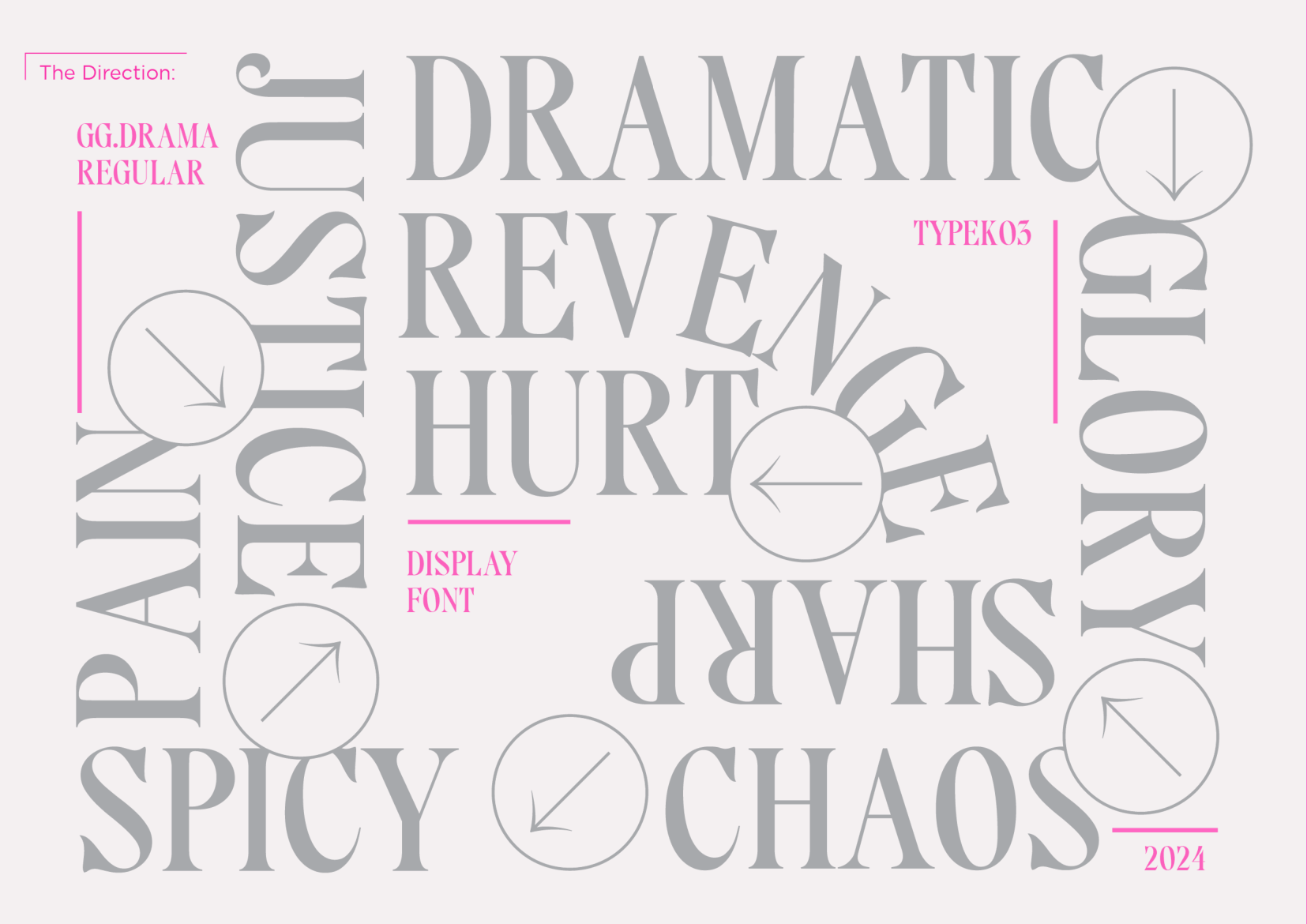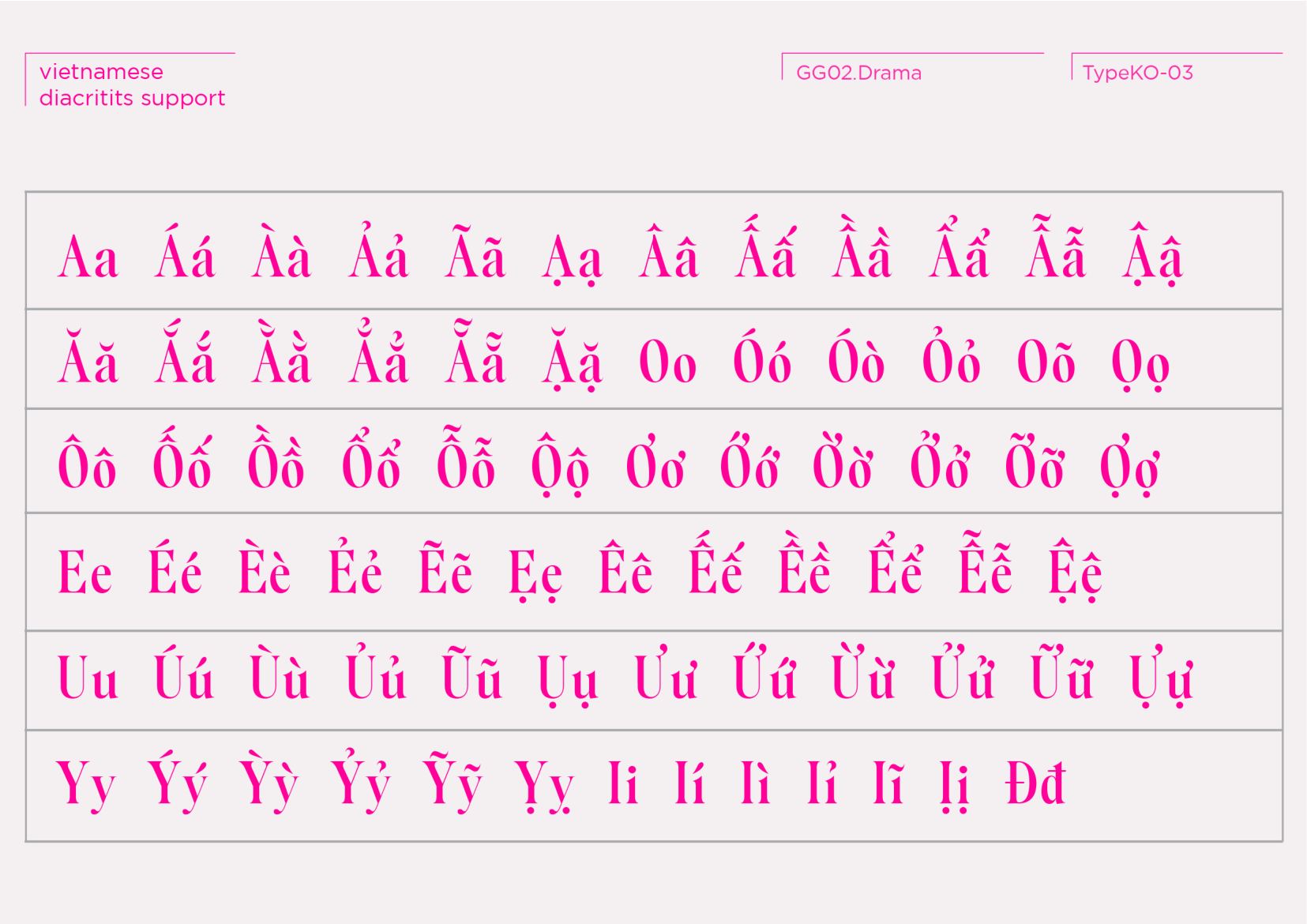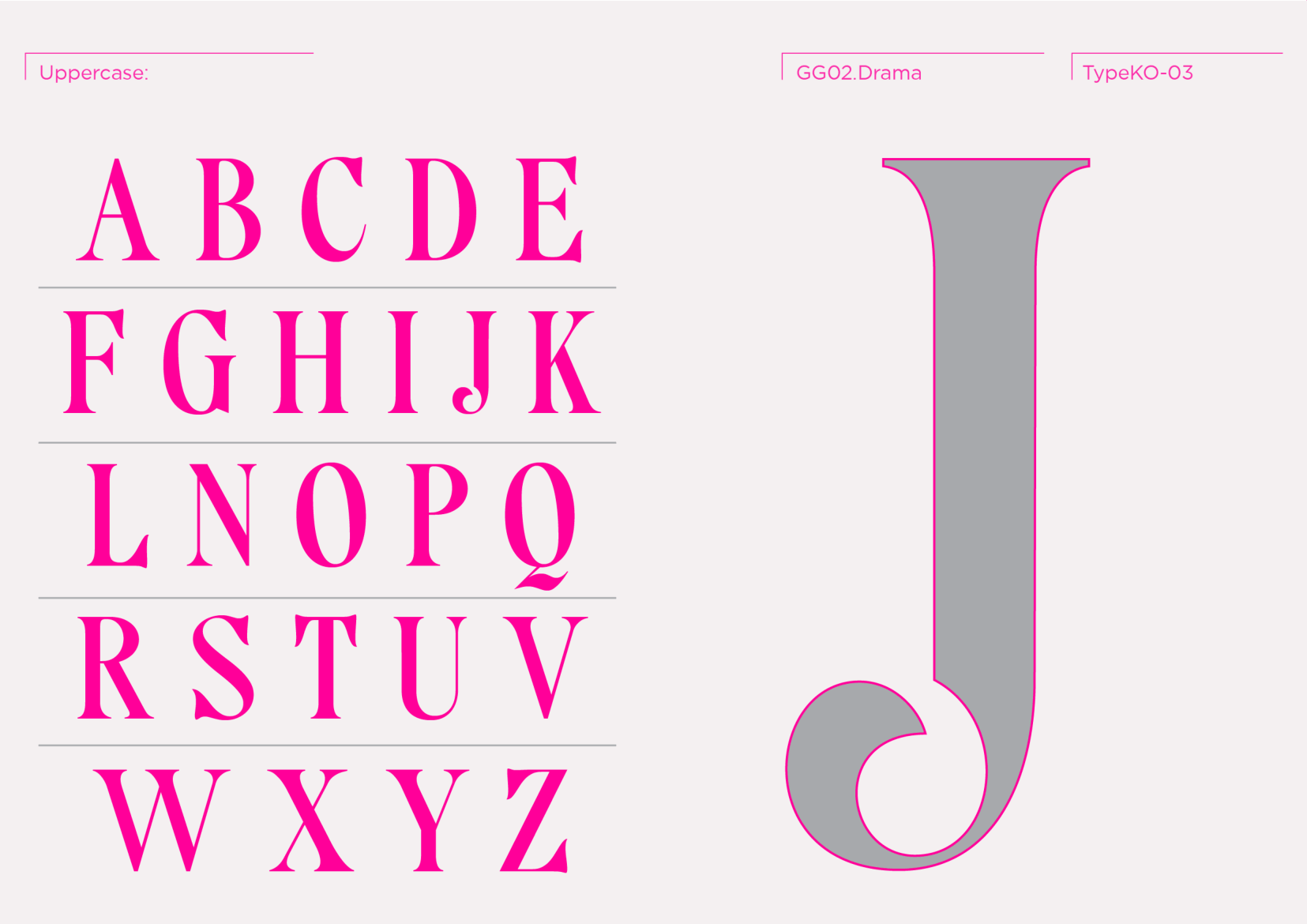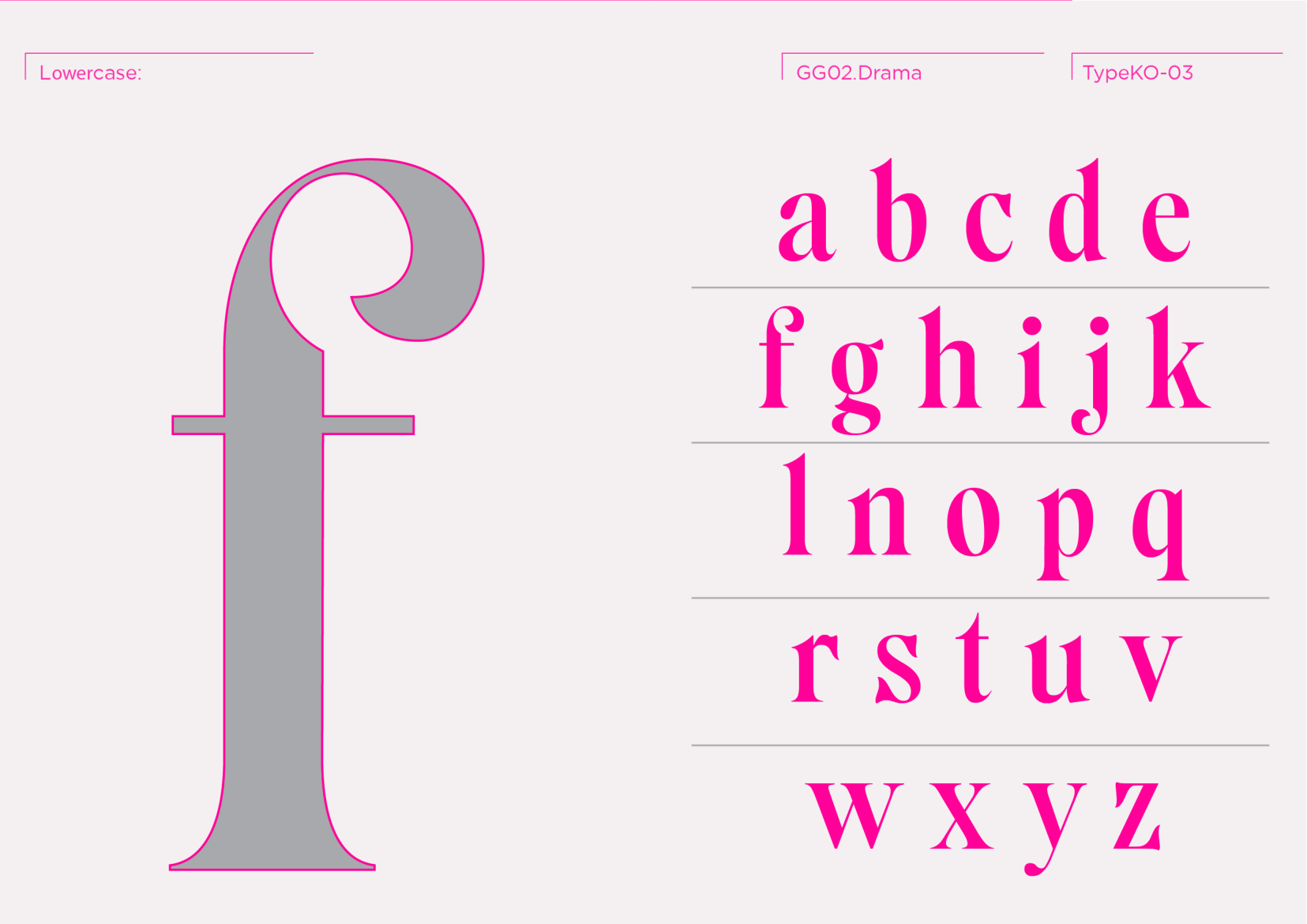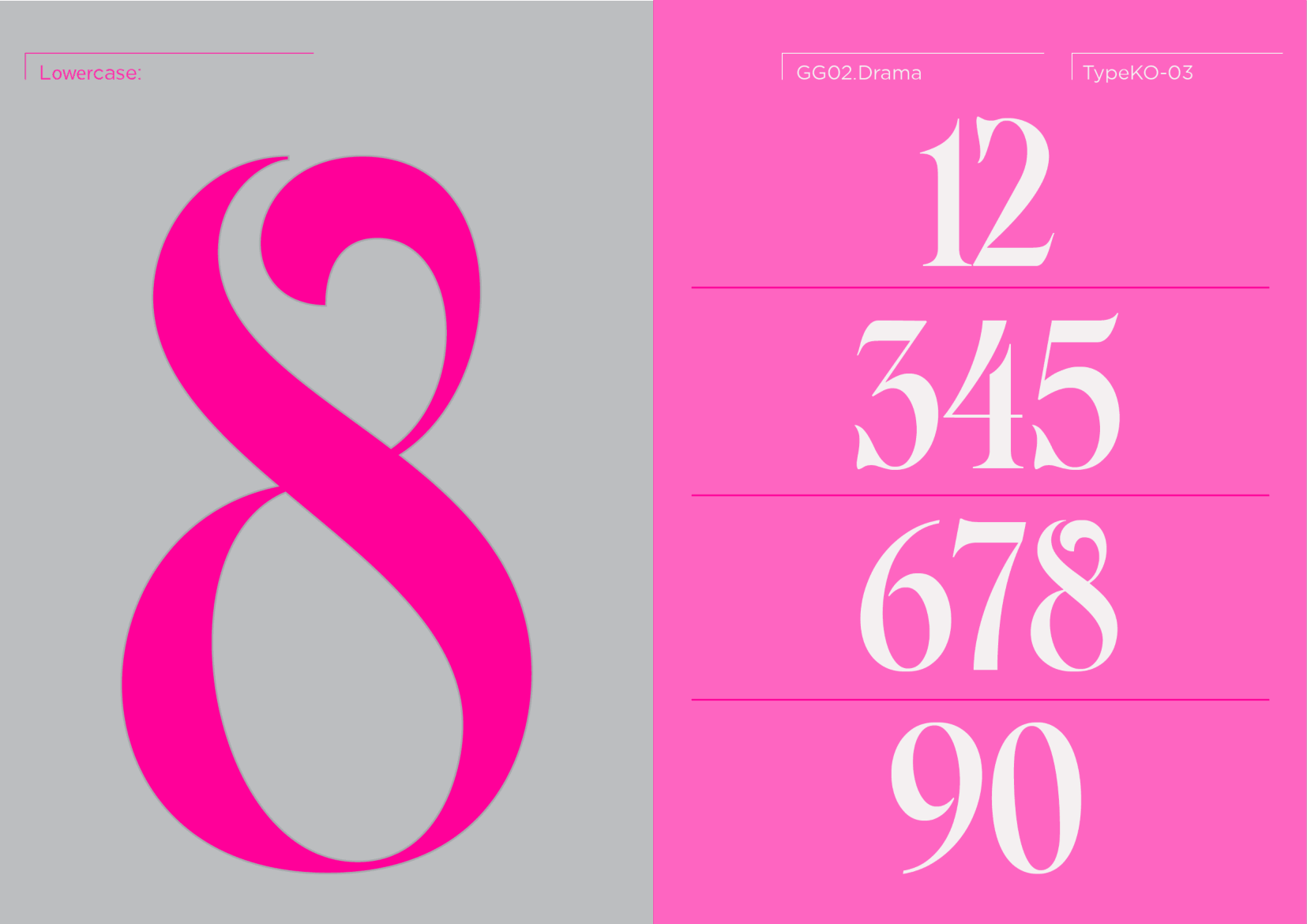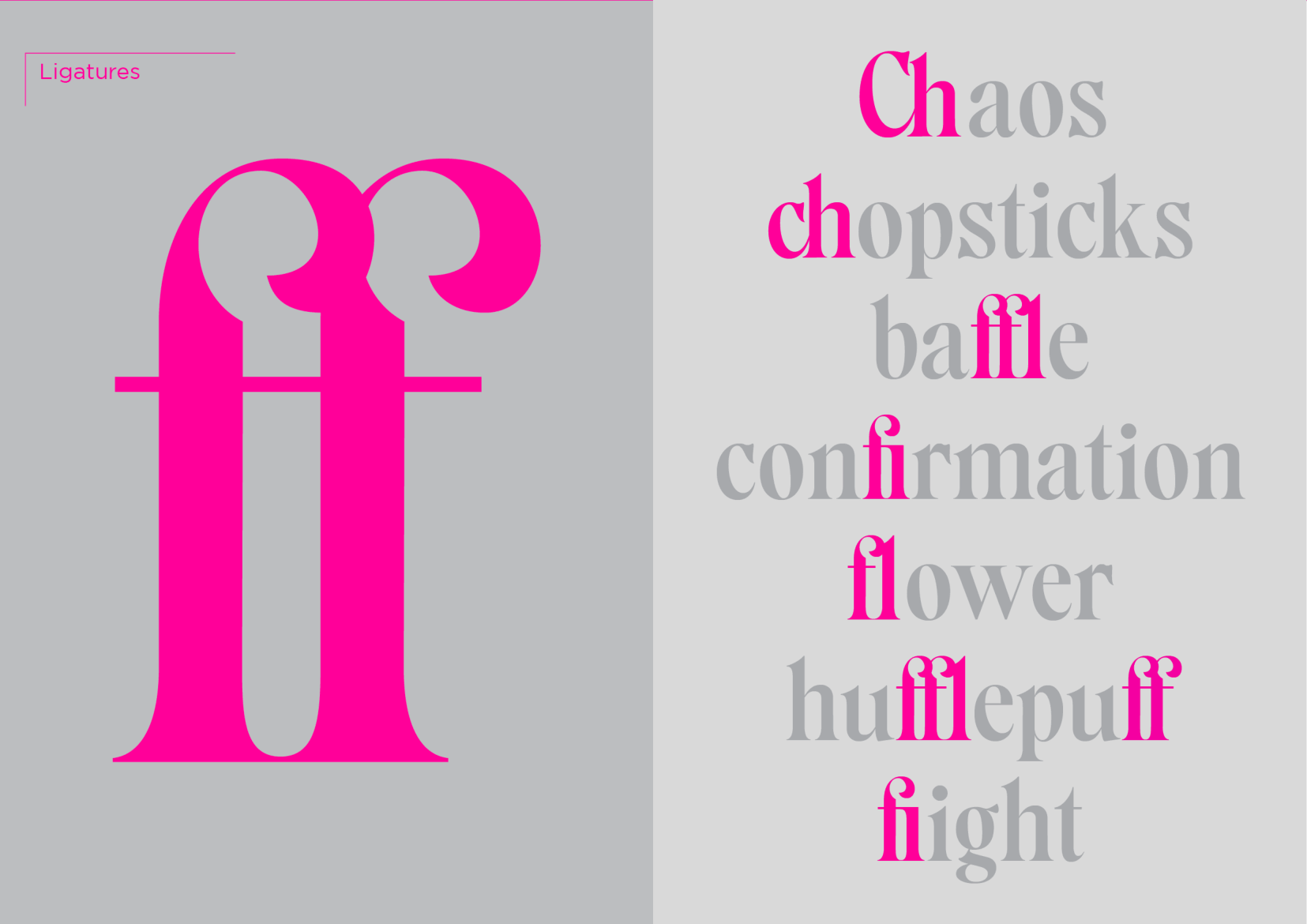
Drama
Về Drama: Phục dựng lại Chicago của Fonderie Turlot với tỷ lệ hẹp hơn, Drama yêu kiều nhón từng bước đài các. Dáng cao, đường nét mềm mại nhưng sắc sảo ở những đoạn uốn vút lên như tơi vô tận. Một vở kịch không ai muốn kết màn.
Transitional Serif
Display
Ngô Thu Giang
Chicago was a display typeface produced by the Fonderie Turlot, one of the most storied Parisian type houses of the 19th century.
Alfred Turlot bought his foundry around 1873, building it on the accumulated type funds of earlier houses including those of Torey, the Virey brothers, Duget and Laurent. By the time Chicago appeared around 1905, Turlot had consolidated several foundries under its roof, including the renowned Derriey, Virey frères, Marcellin-Legrand, Dumeil and Colson collections.